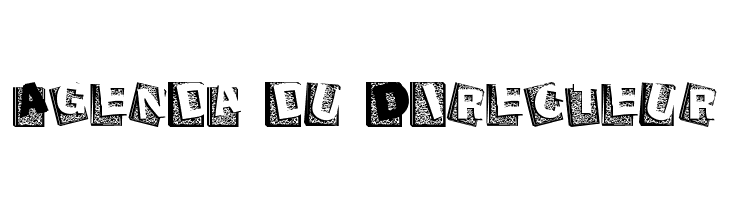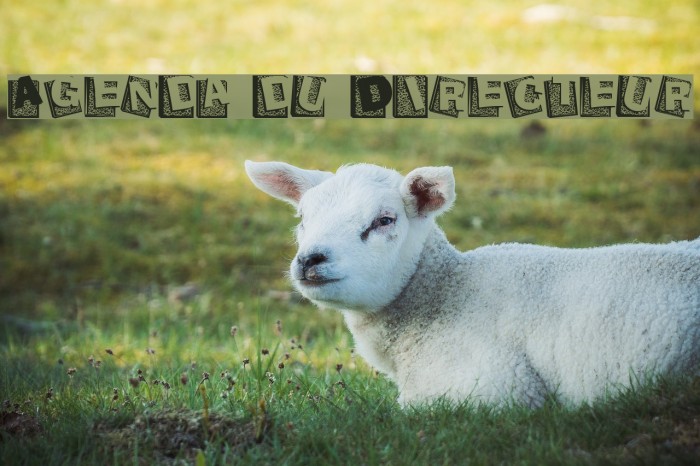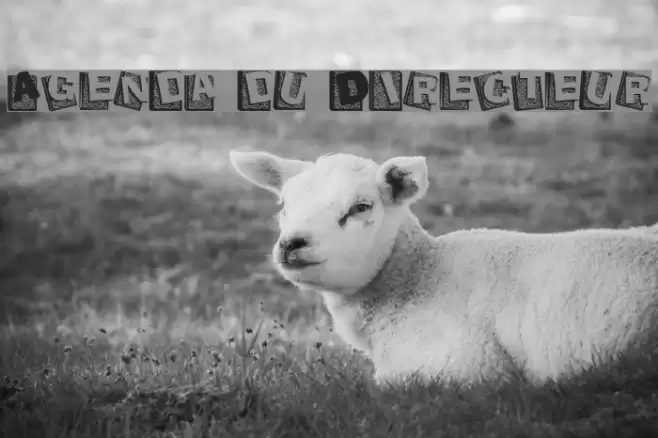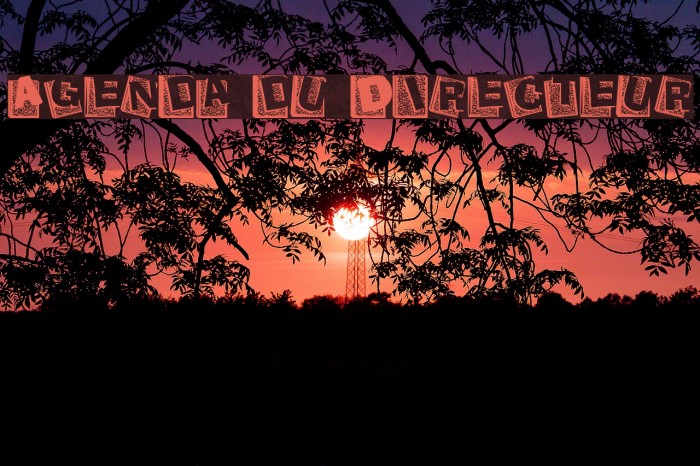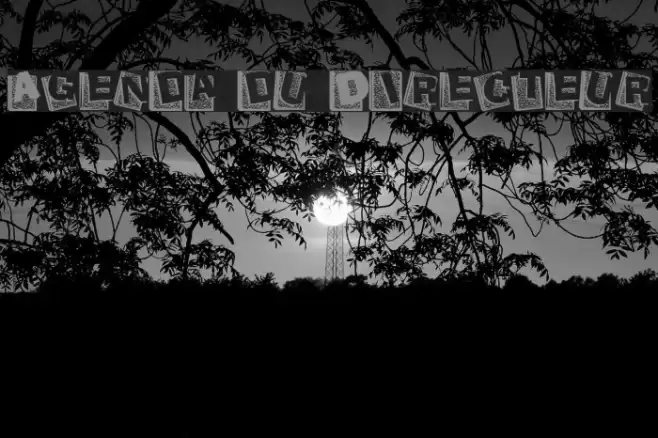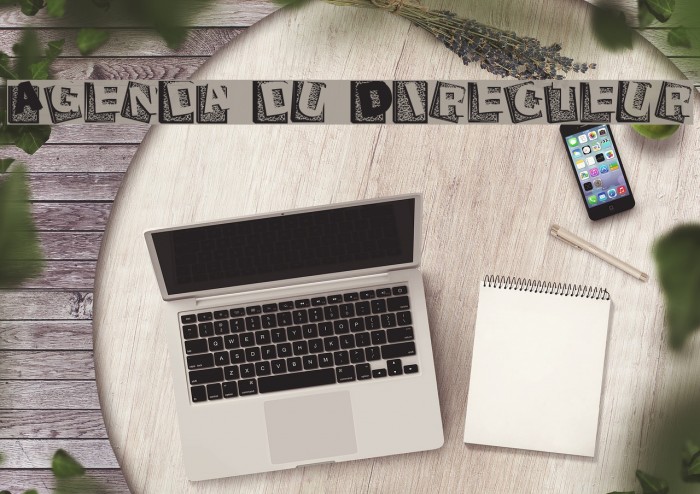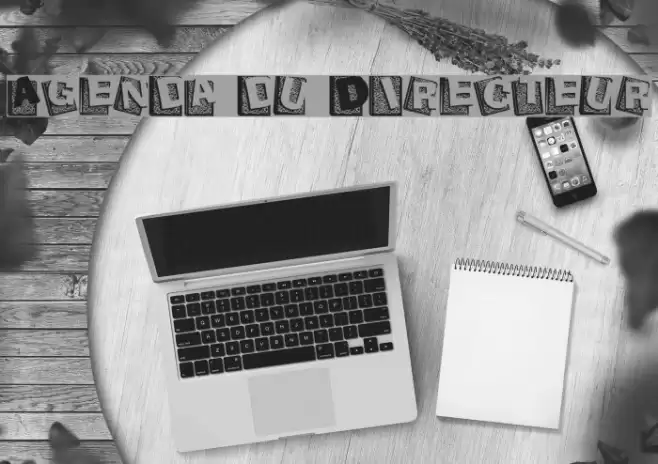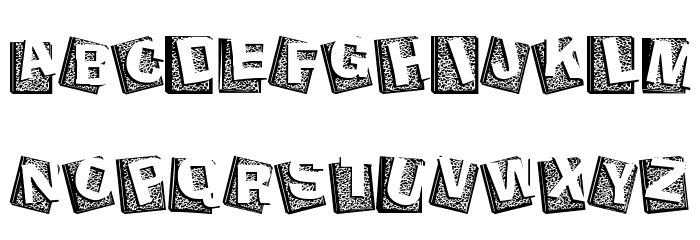
Agenda du Directeur Font
| Estilo general | Playful, Energetic, Textured |
| Caso de uso | Headlines, Posters, Logos |
| Proyectos propuestos | Ideal for children's book covers, playful posters, comic strips, and any design project that requires a fun and energetic vibe. |